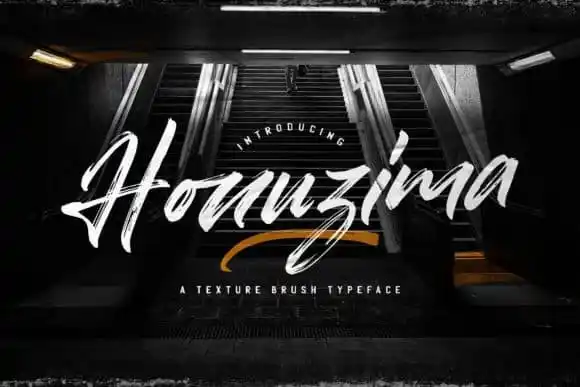
Honuzima Brush Font – Fonte Grátis
Honuzima Brush Font
A Honuzima Brush Font é uma fonte elegante e criativa que combina linhas atraentes com um toque urbano fresco. Desenhada pelo designer StringLabs, esta fonte vem de uma caneta alicate e transmite fluidez e elegância ao estilo de escrita manual. Seu design é perfeito para quem busca um ar único e belo em seus projetos. Esta impressão fluida e sofisticada oferece aos designers a oportunidade de adicionar um toque especial às suas criações, seja em layouts digitais ou impressões físicas. Com sua riqueza estilística, a Honuzima Brush Font é uma ótima escolha para quem busca personalização em cada letra e gosta do brilho das canetas à mão na arquitetura urbana.